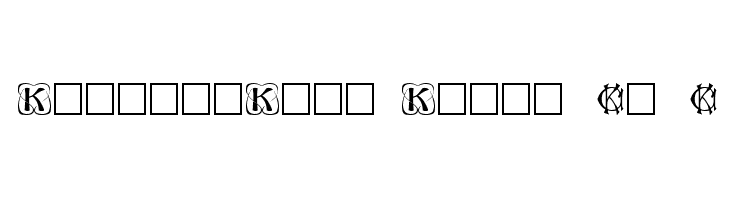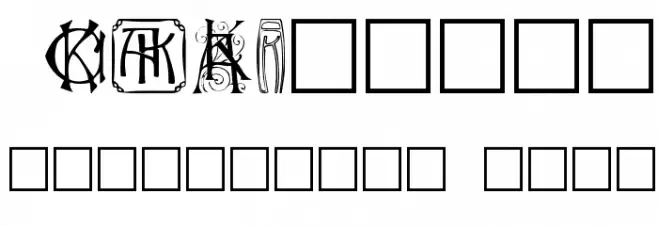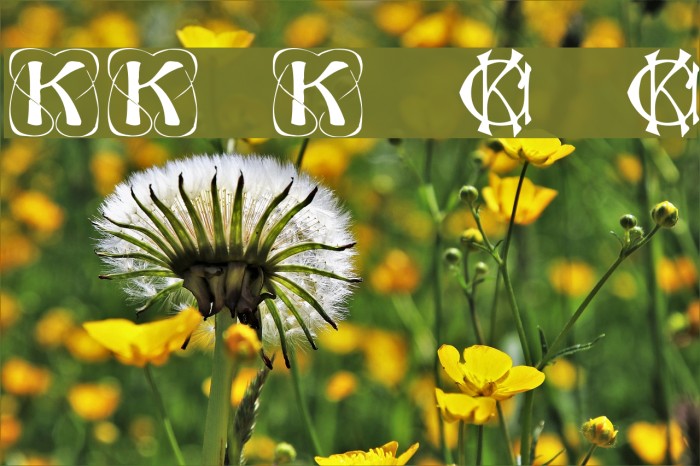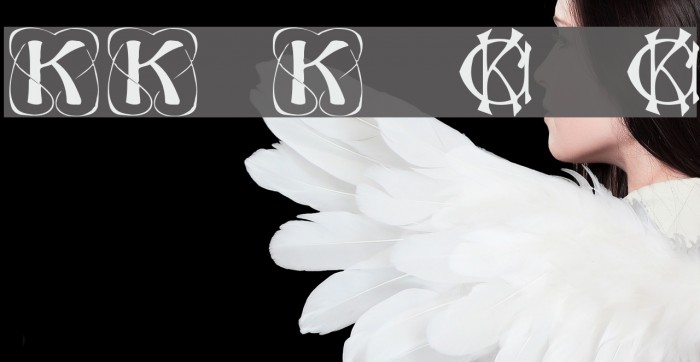
KonanurKaps Kaps:001.001 Font
| Projets proposés | Ideal for vintage-themed posters, decorative invitations, branding for luxury products, or artistic book covers. |